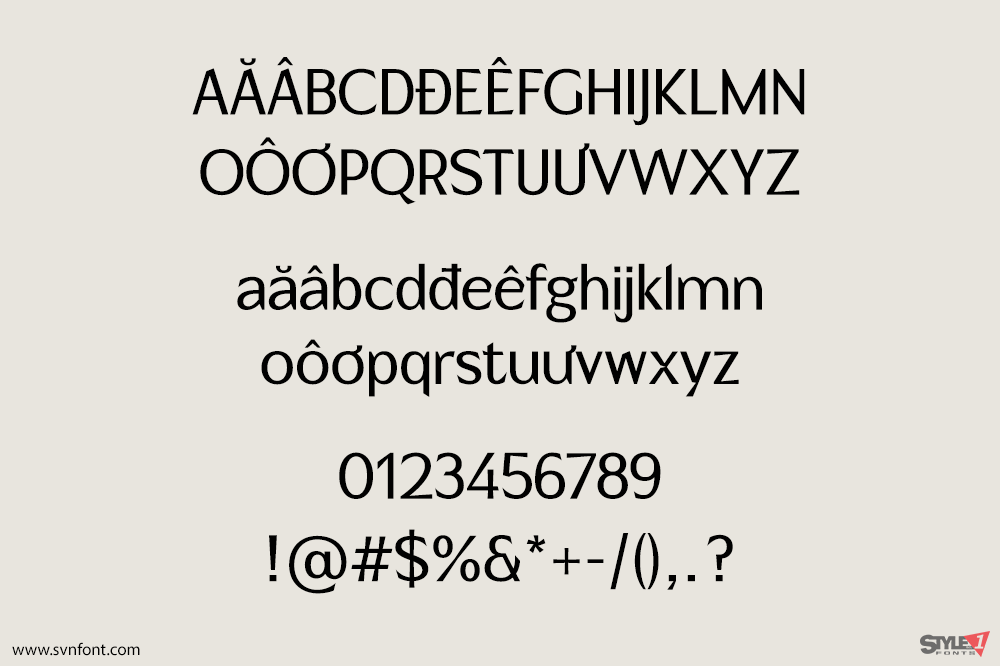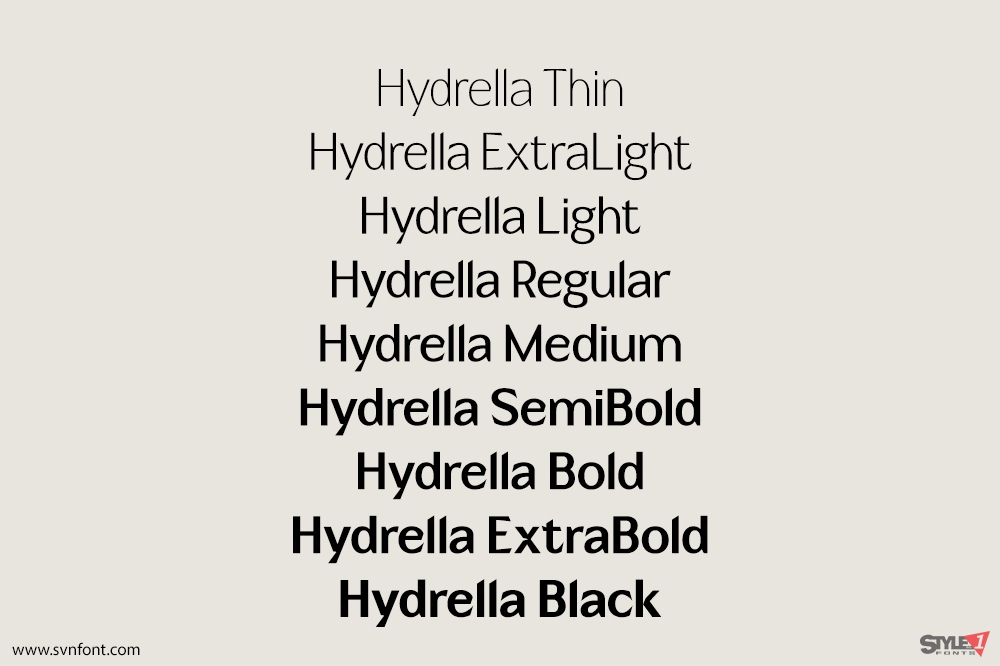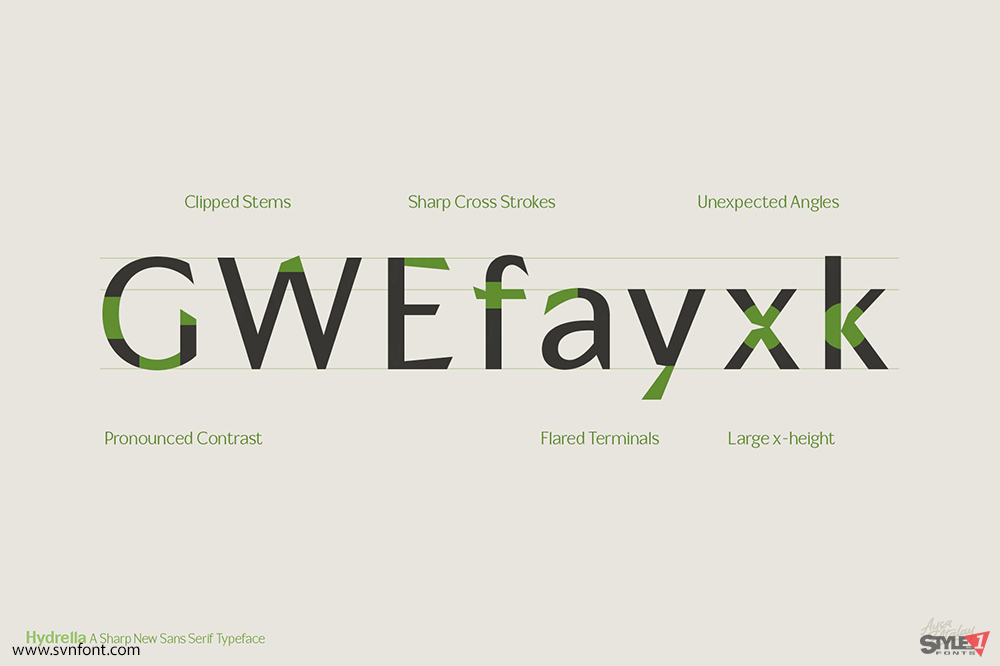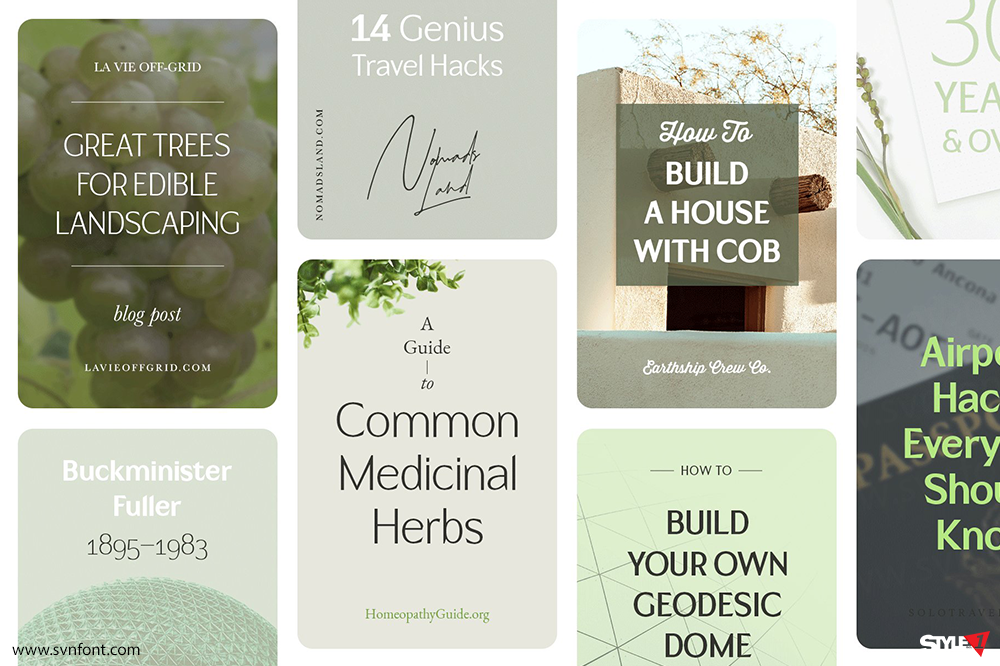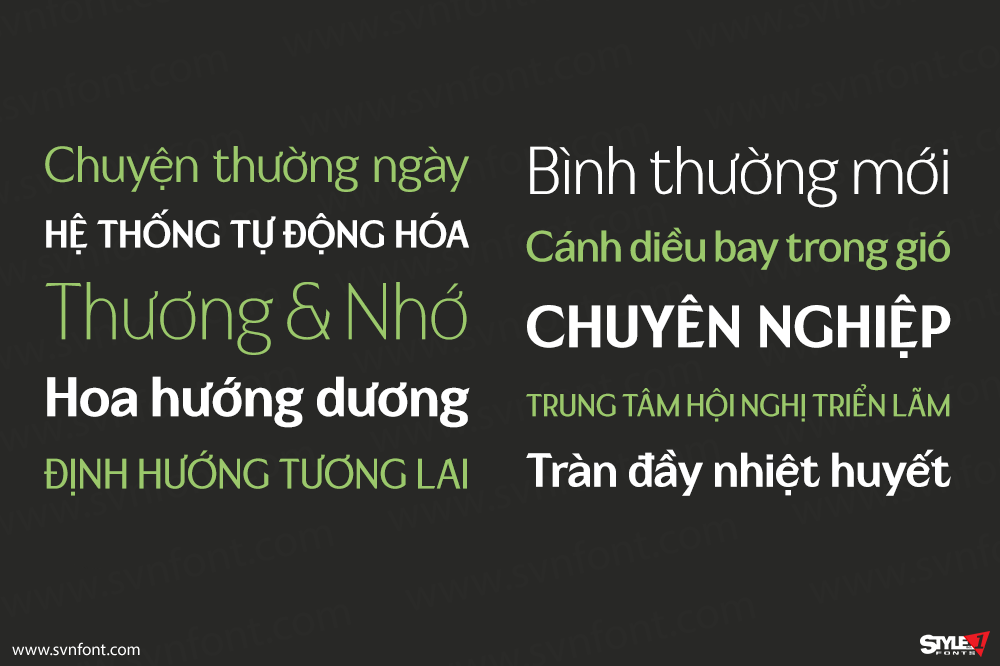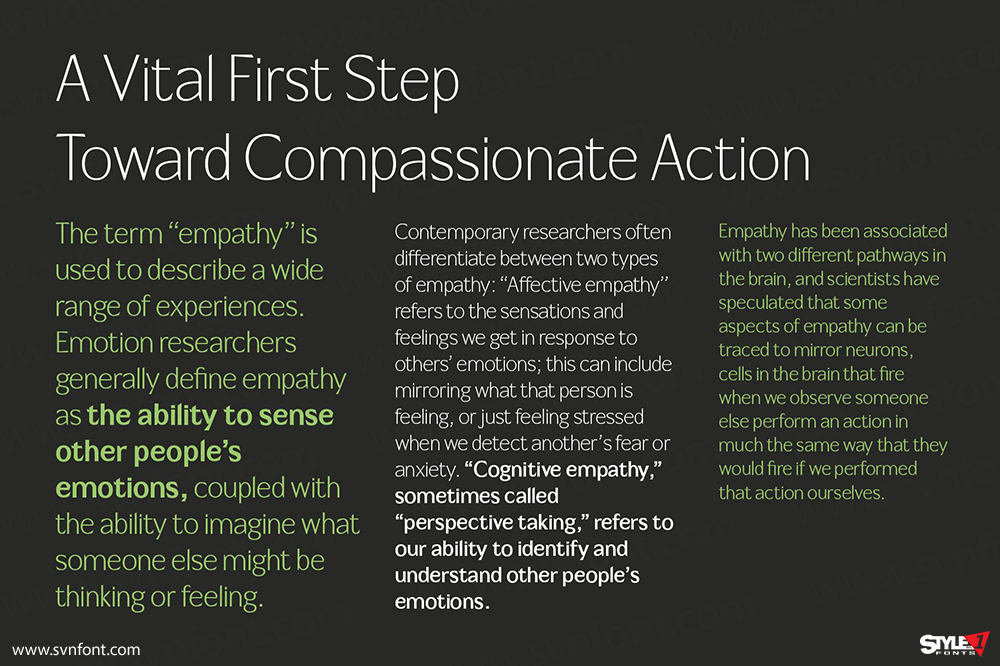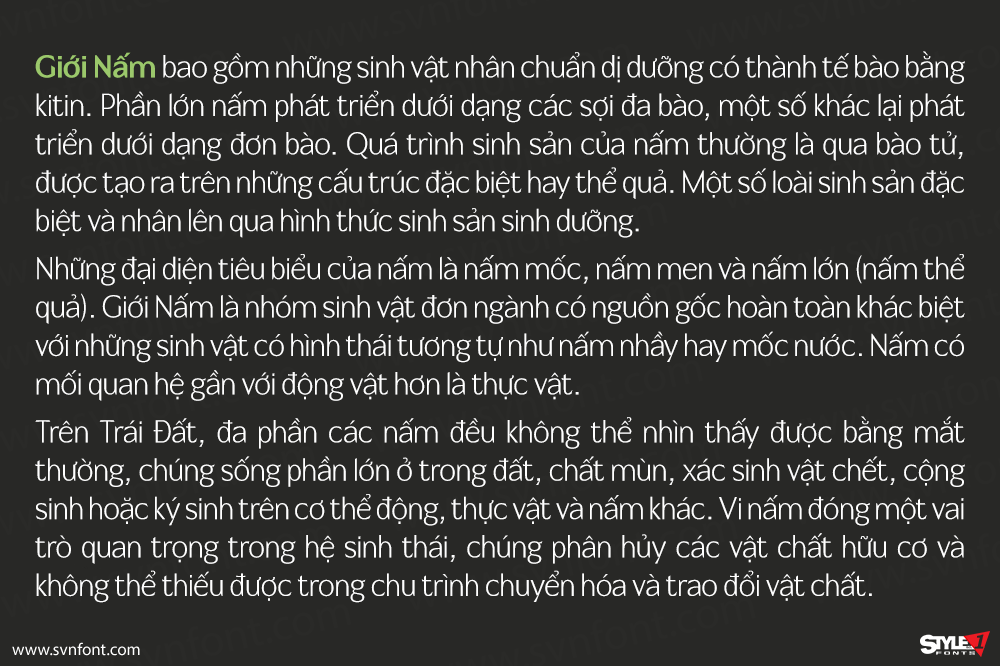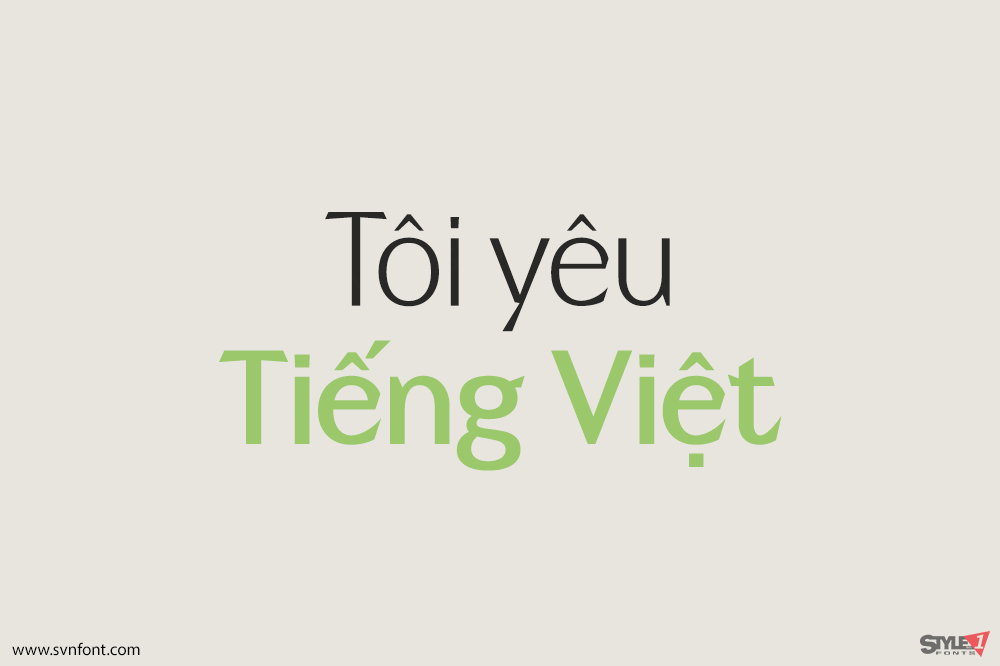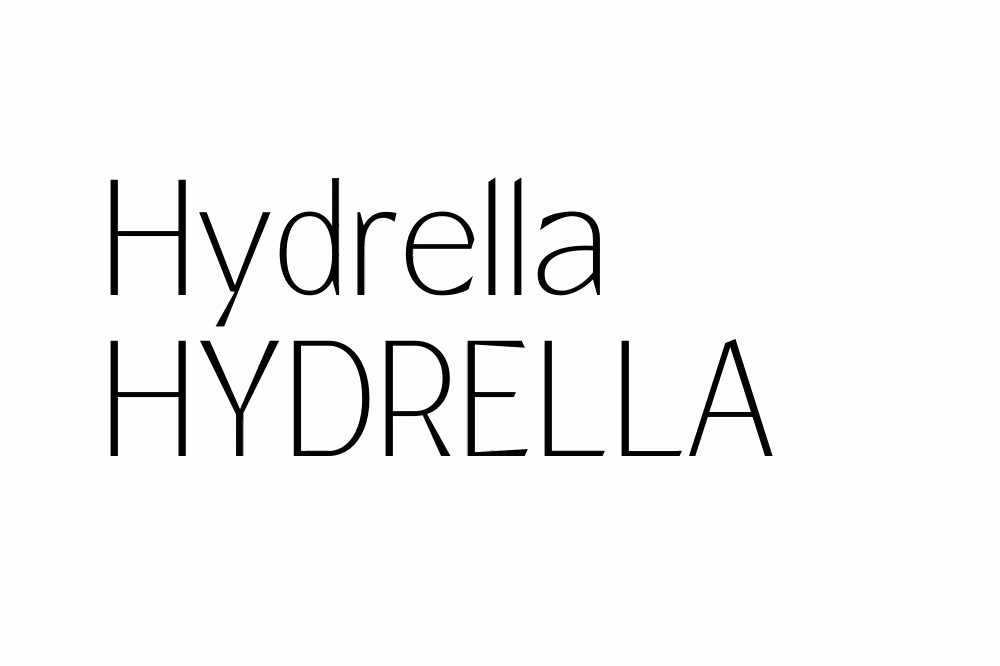
Hydrella là một kiểu chữ sans serif hiện đại với các đặc điểm sắc nét, độc đáo và độ tương phản vừa phải. Những thuộc tính dễ nhận biết của nó mang lại một diện mạo mới mẻ vừa đủ mà không làm lu mờ tổng thể thiết kế. Có sẵn với 9 độ dày, Hydrella hoạt động tốt cả khi làm font hiển thị và ở các kích thước nhỏ hơn.
Nhà thiết kế: Ayça Atalay
Nhà phát hành: Ayça Atalay